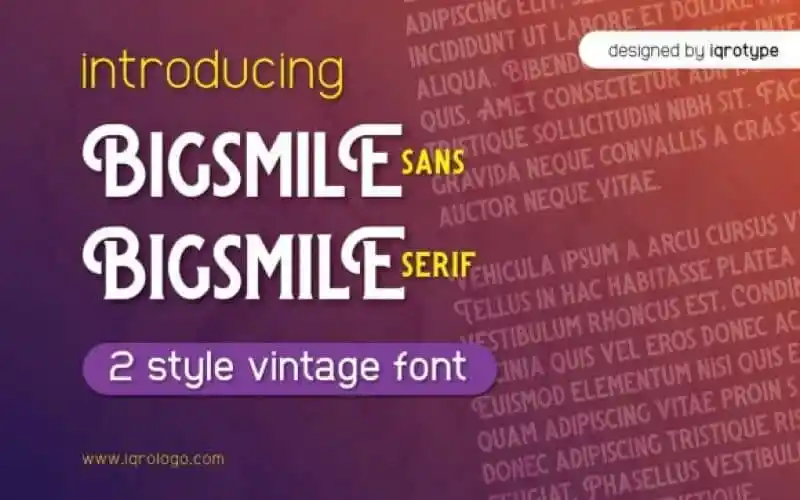
Bigsmile Font Duo – Fonte Grátis
Bigsmile Font Duo
A Bigsmile Font Duo é uma escolha perfeita para projetistas que buscam uma fonte moderna e versátil para trabalhos diários. Este tipo de fonte com dois estilos diferentes oferece um nível extra de flexibilidade, adequada tanto para títulos em grandes dimensões quanto para textos menores, tornando-a ideal para diversos usos. A Bigsmile foi projetada pelo iqrotype e compartilhada pela 99designs, uma plataforma conhecida por seus recursos de design. Esta fonte é especialmente útil para ambientes onde a criatividade está em alta estima, como projeto de marca, criação de produtos home-ware ou embalagens, design de capas de revistas e até mesmo como overlay de texto para imagens no fundo. Com apenas duas opções de estilo, a fonte Bigsmile Duo oferece uma alternativa versátil que pode transformar qualquer projeto em algo ainda mais especial.